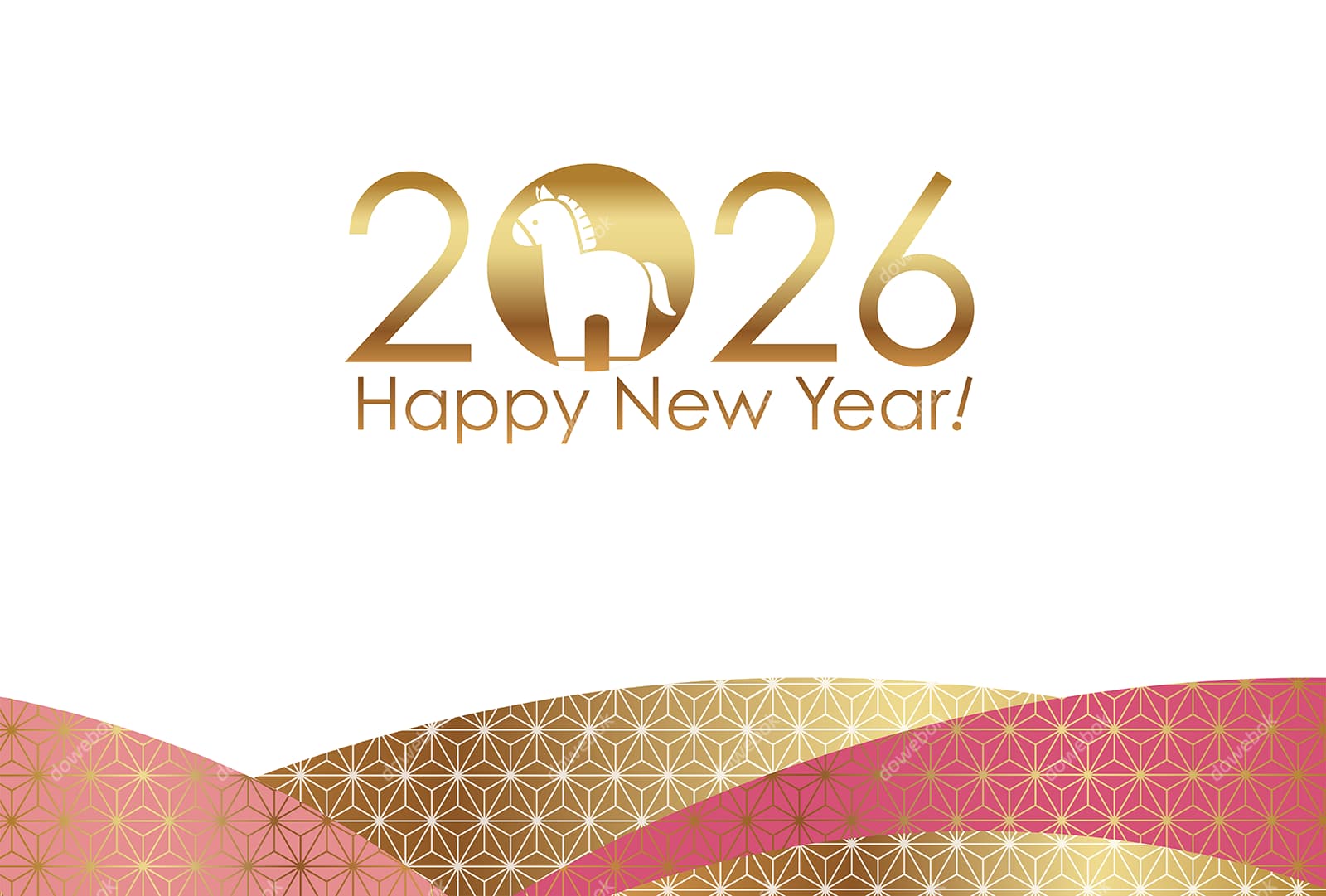
这是一款 2026 丙午马年新春设计矢量素材,纯白背景简洁清爽,鎏金 “2026” 字体中,数字 “0” 嵌着白描小马剪影,契合马年生肖。下方 “Happy New Year!” 字样呼应节日主题,底部粉金渐变的日式几何纹底纹添了雅致质感。整体以简约配色融合生肖元素与传统纹样,既显春节的清新氛围,又透出精致的节日仪式感。